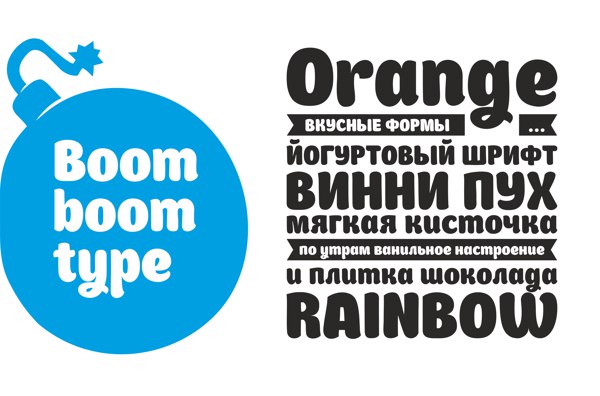
Декоративный шрифт Boomboom! Отлично подойдет для оформления ярких упаковок, афиш, постеров и флаеров.
Шрифт является дипломной работой Anna Vasilieva (behance.net/AnnaVasilieva) в Британской высшей школе дизайна.